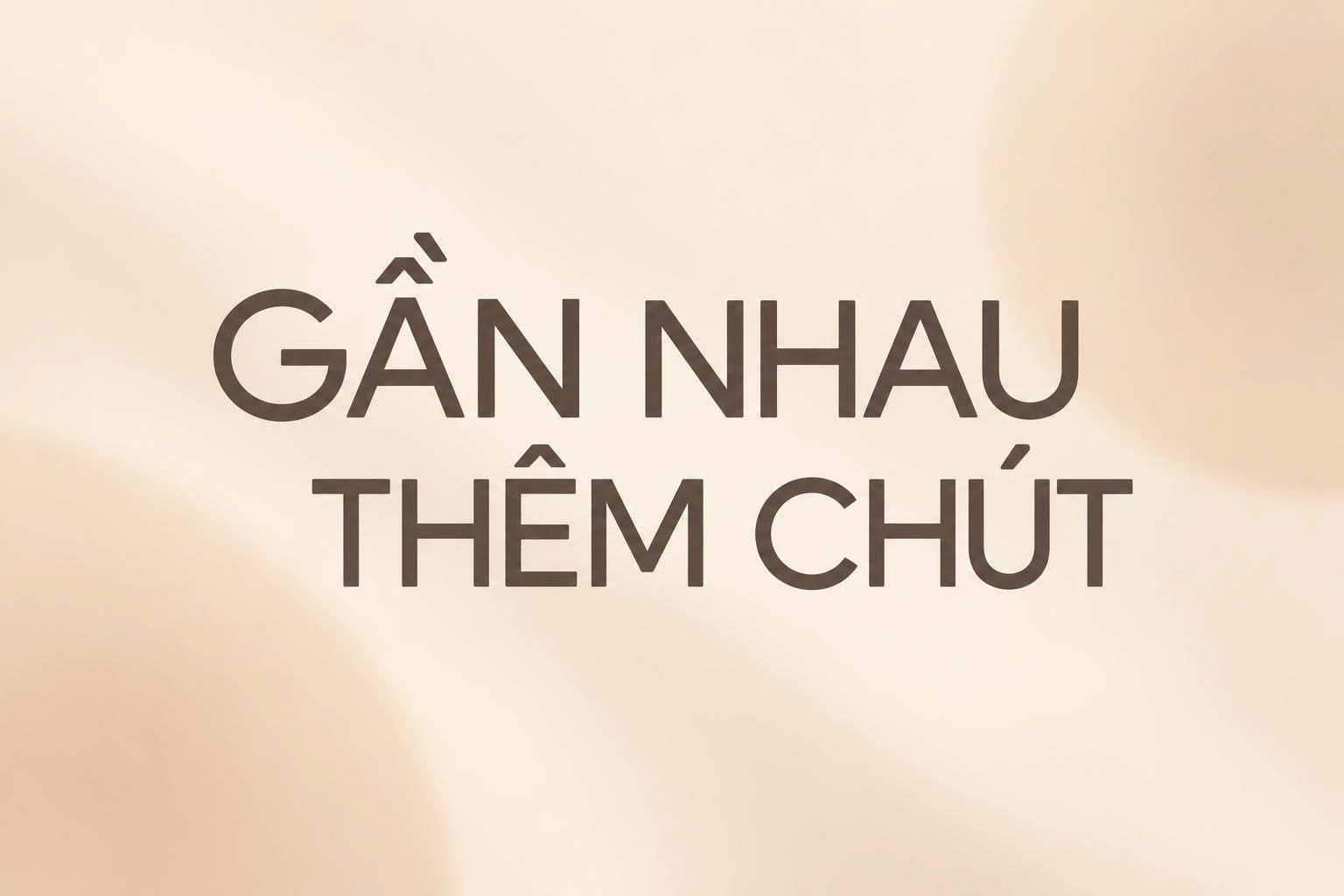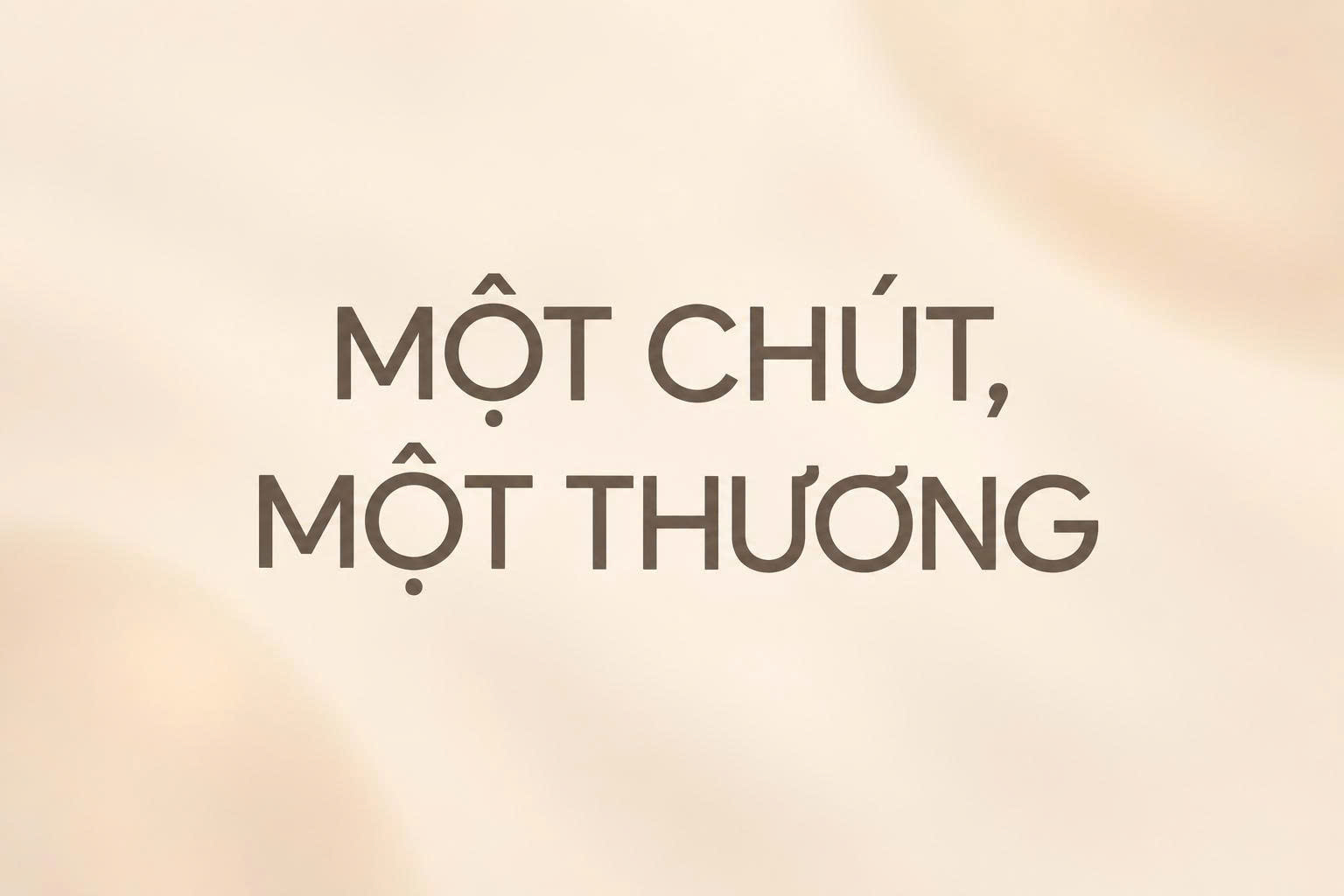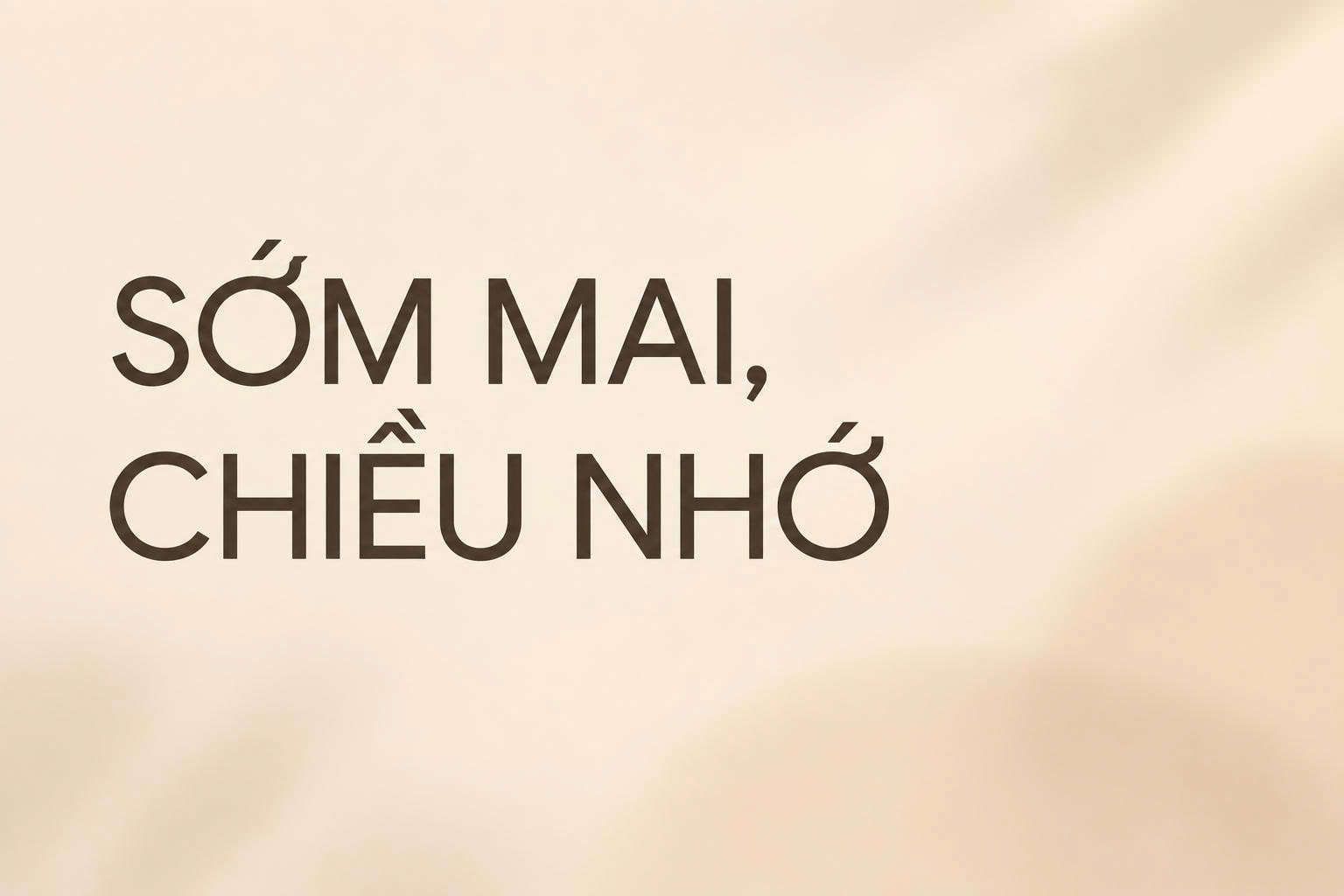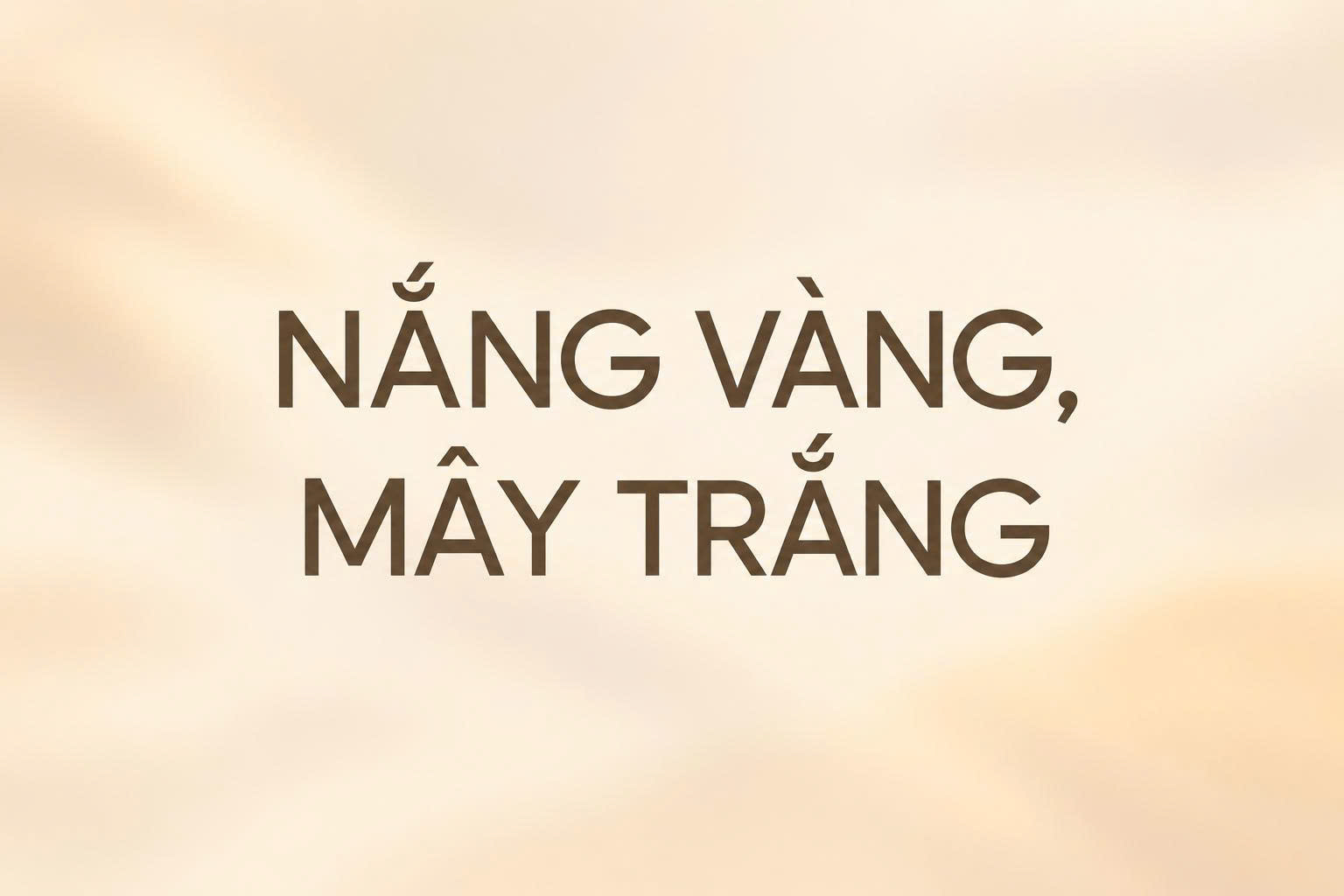
Download font Google Sans là từ khóa được giới designer săn đón hàng đầu khi cần một bộ phông chữ không chân (Sans-serif) hiện đại, tối giản và mang tính biểu tượng của sự đổi mới. Được Google phát triển dựa trên bộ Product Sans kinh điển, Google Sans đã được tinh chỉnh để tối ưu hóa khả năng hiển thị trên nhiều kích thước khác nhau. Doozypack.vn cung cấp link tải font Google Sans trọn bộ đã được Việt hóa chỉn chu, giúp bạn sở hữu phông chữ đẳng cấp để thiết kế bao bì và bộ nhận diện thương hiệu chuyên nghiệp mà không lo lỗi dấu tiếng Việt.
Đặc điểm thiết kế đột phá của bộ font Google Sans
Google Sans không chỉ là một phông chữ; nó là ngôn ngữ thiết kế của tương lai, mang lại diện mạo vô cùng sạch sẽ và uy tín cho mọi sản phẩm đồ họa.
Mẫu chữ Google Sans hiện đại
Phong cách Geometric Sans-serif chuẩn mực
Đặc trưng lớn nhất của google sans download font là cấu trúc chữ dựa trên các hình khối hình học chuẩn xác nhưng được xử lý với các đường cong “nhân văn” (humanist). Điều này giúp các ký tự như ‘a’, ‘g’, ‘e’ trông rất thân thiện, dễ tiếp cận nhưng vẫn giữ được tính kỷ luật của kỹ thuật. Phông chữ này mang lại cảm giác minh bạch, cực kỳ phù hợp với các thương hiệu hướng đến khách hàng trẻ và các sản phẩm công nghệ thông minh.
Khả năng hiển thị sắc nét từ màn hình đến bản in
Khác với bản Product Sans chỉ dùng cho logo, font Google Sans được thiết kế để đọc tốt ở mọi kích thước. Nhờ khoảng hở trong chữ (counter) được tính toán tỉ mỉ, phông chữ này duy trì được độ rõ nét tuyệt vời ngay cả khi in ở kích thước nhỏ trên tem nhãn decal dán sản phẩm. Khi bạn tải font google bản Việt hóa tại Doozypack.vn, hệ thống dấu thanh đã được tinh chỉnh hài hòa, không làm mất đi nhịp điệu hình học đặc trưng của font gốc.
Tại sao designer nên tải font Google Sans Việt hóa cho bao bì?
Trong ngành thiết kế và sản xuất bao bì tại Doozypack.vn, Google Sans luôn nằm trong danh mục các font chữ “vàng” nhờ tính ứng dụng thực tế cao:
• Xây dựng sự uy tín: Vẻ ngoài hiện đại và sạch sẽ của Google Sans giúp bao bì toát lên vẻ chuyên nghiệp, tạo niềm tin cho người tiêu dùng ngay từ cái nhìn đầu tiên.
• Giải quyết lỗi hiển thị: Việc download font google sans bản Việt hóa chuẩn giúp bạn gõ các slogan như “Công nghệ dẫn đầu” hay “Sản phẩm chính hãng” một cách trọn vẹn, không bị nhảy font ở các ký tự có dấu đặc thù.
• Tính đa dụng vượt trội: Bạn có thể dùng Google Sans cho cả Logo, tiêu đề chính lẫn các đoạn văn bản hướng dẫn sử dụng mà vẫn đảm bảo tính thẩm mỹ đồng bộ.
Kiểu chữ tối giản tinh tế
Biến thể Font Đặc điểm thị giác Ứng dụng đề xuất tại Doozypack.vn
Google Sans Light Thanh mảnh, thanh lịch Dùng cho ghi chú phụ, địa chỉ sản xuất trên vỏ hộp.
Google Sans Regular Cân đối, dễ đọc Dùng cho nội dung mô tả, bảng thành phần dinh dưỡng.
Google Sans Medium/Bold Vững chãi, nổi bật Dùng làm tiêu đề chính, tên sản phẩm hoặc logo thương hiệu.
03 Ứng dụng của font Google Sans trong sản xuất bao bì thực tế
Sự hiện đại và minh bạch của Google Sans mang lại hiệu quả thị giác đặc biệt trên các ấn phẩm tại Doozypack.vn:
• Hộp sản phẩm công nghệ: Nét chữ hình học chuẩn xác của Google Sans rất tương đồng với các thiết kế đồ điện tử hiện đại, tạo nên sự đồng bộ chuyên nghiệp từ sản phẩm đến vỏ hộp.
• Bao bì thực phẩm sạch (Organic): Độ minh bạch của Google Sans gợi cảm giác an toàn, uy tín cho các dòng sản phẩm có nguồn gốc từ thiên nhiên.
• Túi giấy doanh nghiệp: Tên công ty in bằng font google sans Bold trên túi giấy Ivory cán màng mờ tạo cảm giác vững chắc và tin cậy cho thương hiệu.
Thiết kế typography gọn gàng
Lưu ý kỹ thuật khi in ấn với phông chữ Google Sans
Sản xuất bao bì sử dụng phông chữ đặc thù như Google Sans đòi hỏi designer cần lưu ý một số vấn đề kỹ thuật tại xưởng in chuyên nghiệp:
• Kiểm soát độ tràn mực (Dot Gain): Do các khe hở trong chữ của Google Sans khá thoáng, phông chữ này rất an toàn khi in Offset. Tuy nhiên, trên giấy Kraft, bạn nên để size chữ tối thiểu từ 6pt trở lên.
• Hệ màu CMYK cho văn bản: Luôn thiết kế trên hệ màu CMYK. Đối với chữ màu đen nhỏ, hãy sử dụng thông số K=100 để chữ sắc nét nhất, tránh hiện tượng nhòe màu (lé bản kẽm) khi in chồng nhiều màu.
5. In font Google Sans kích thước nhỏ trên hộp giấy có bị mờ không?